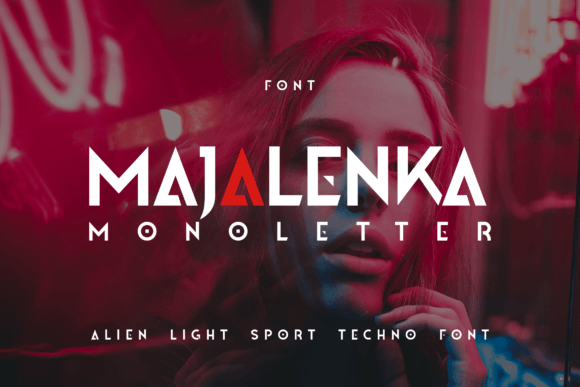
Majalenka Monoletter
Jika anda sedang mencari aset berkualiti tinggi seperti Majalenka Monoletter, pakej premium ini merupakan pilihan yang hebat untuk projek kreatif anda.
Dicipta dengan ketepatan, Majalenka Monoletter menyediakan vektor yang bersih, tipografi yang licin dan lesen komersial untuk ketenangan fikiran.
Sama ada anda mencipta produk POD (Print on Demand), jemputan perkahwinan atau grafik media sosial, Majalenka Monoletter amat bersesuaian.